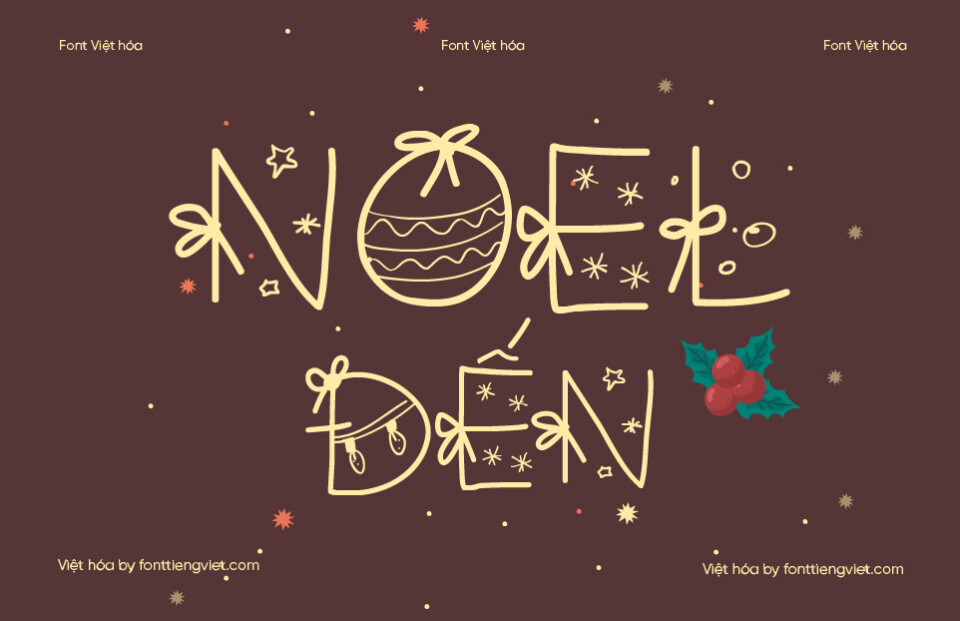
Font Việt hóa 1FTV VIP PWChristmas
Tải Font Việt hóa 1FTV VIP PWChristmas Miễn Phí Đón Giáng Sinh Lung Linh
Giới thiệu về Font Việt hóa 1FTV VIP PWChristmas
Mùa lễ hội cuối năm luôn là thời điểm tuyệt vời để các bạn học sinh và thầy cô trang trí lớp học hay làm thiệp chúc mừng. Để những thiết kế thêm phần sinh động, việc lựa chọn một bộ Font Chữ phù hợp là vô cùng quan trọng. Trong đó, Font Việt hóa 1FTV VIP PWChristmas nổi lên như một lựa chọn hàng đầu nhờ phong cách lễ hội đặc trưng, mang đậm không khí ấm áp của mùa Noel. Bộ font này không chỉ giúp các văn bản trở nên bắt mắt mà còn truyền tải trọn vẹn thông điệp yêu thương đến người nhận thông qua những đường nét uốn lượn tinh tế và sáng tạo.
Đặc điểm nổi bật của bộ Font Việt hóa 1FTV VIP PWChristmas
Thiết kế đậm chất Giáng sinh
Font Việt hóa 1FTV VIP PWChristmas được thiết kế với các ký tự đi kèm hình ảnh trang trí như bông tuyết, mũ ông già Noel hay những dải ruy băng xinh xắn. Điều này giúp người dùng tiết kiệm thời gian thiết kế thêm các họa tiết phụ trợ. Với bản Việt hóa hoàn chỉnh, các bạn có thể yên tâm gõ tiếng Việt có dấu mà không lo bị lỗi hiển thị hay mất nét, đảm bảo tính thẩm mỹ cao nhất cho mọi sản phẩm đồ họa từ đơn giản đến phức tạp.
Ứng dụng trong học tập và sáng tạo
Bộ phông chữ này cực kỳ phù hợp để làm báo tường, thiết kế slide bài giảng chủ đề mùa đông hoặc tạo ra những tấm thiệp mời dự tiệc Giáng sinh tại trường. Sự kết hợp giữa tính nghệ thuật và sự gần gũi giúp nó dễ dàng chinh phục mọi ánh nhìn. Bạn có thể sử dụng font này trên nhiều phần mềm khác nhau như Photoshop, Canva hay thậm chí là Microsoft Word để tạo nên sự khác biệt cho nội dung của mình.